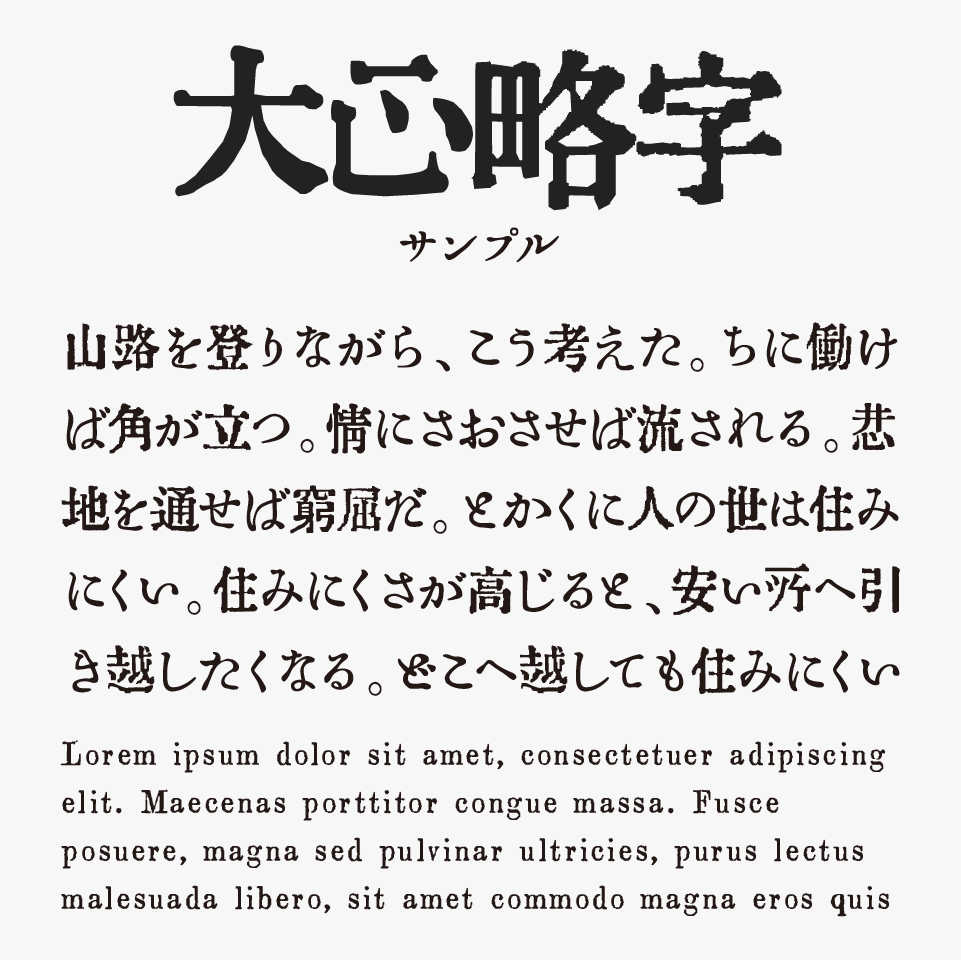
大正略字フォント
大正略字フォントは、「大正活字っぽい?フォント」をベースに別のフォントを混植して、大正時代の活字を目指して制作されたフォントです。
一部の文字には、当時の文献や印刷物を参考にした略字表現が取り入れられており、現代のフォントにはない独特な空気感があります。文字ごとに少しずつ異なるニュアンスが混ざることで、古書や古い広告のような味わい深さを感じられるのも魅力です。
輪郭にはインクのにじみや擦れを思わせる加工が施されており、活版印刷ならではのざらついた質感まで丁寧に再現されています。活字のカッコよい表現がフォントで再現されているフォントです。
一部の文字を大正期の主に書物に載っている略字等にデザインされているので、普段見慣れている文字と少し違い文字がありますが、これがこのフォントの特長です。